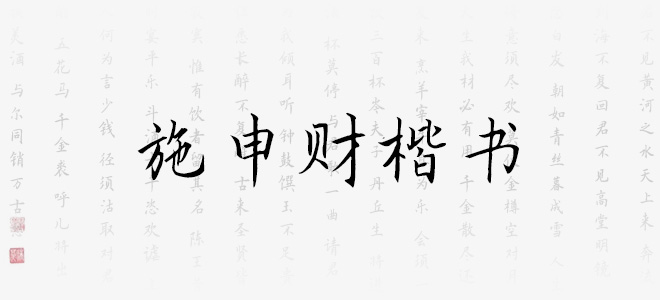
施申財(cái)楷書是由施申財(cái)老師繪制的楷書字體,字體線條粗細(xì)適中,筆畫嚴(yán)謹(jǐn),結(jié)構(gòu)端正,具有很好的視覺感,適合于文化類的宣傳設(shè)計(jì)、商業(yè)類品牌的廣告和產(chǎn)品包裝設(shè)計(jì)以及個(gè)性化文字排版等較多場景。
施申財(cái)楷書